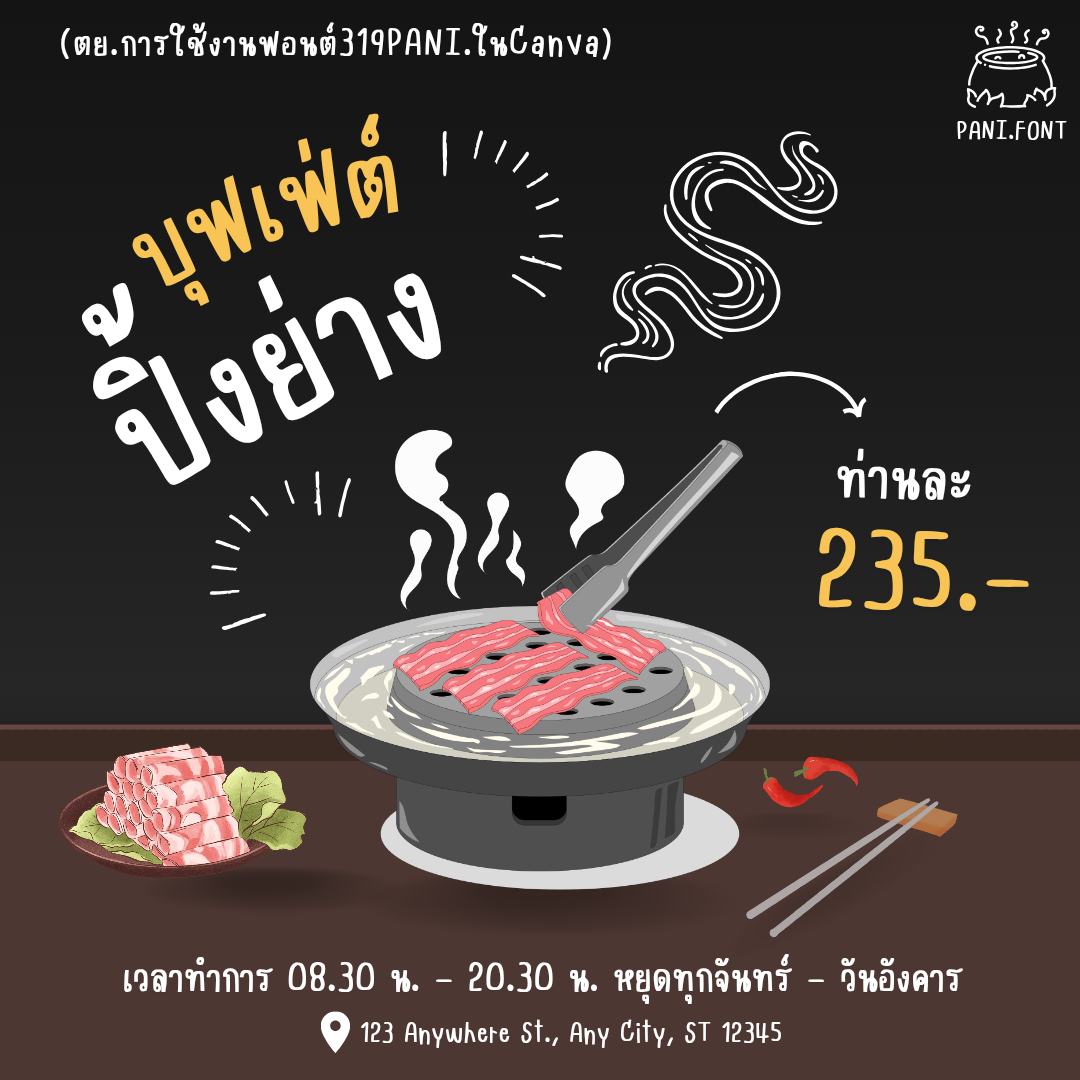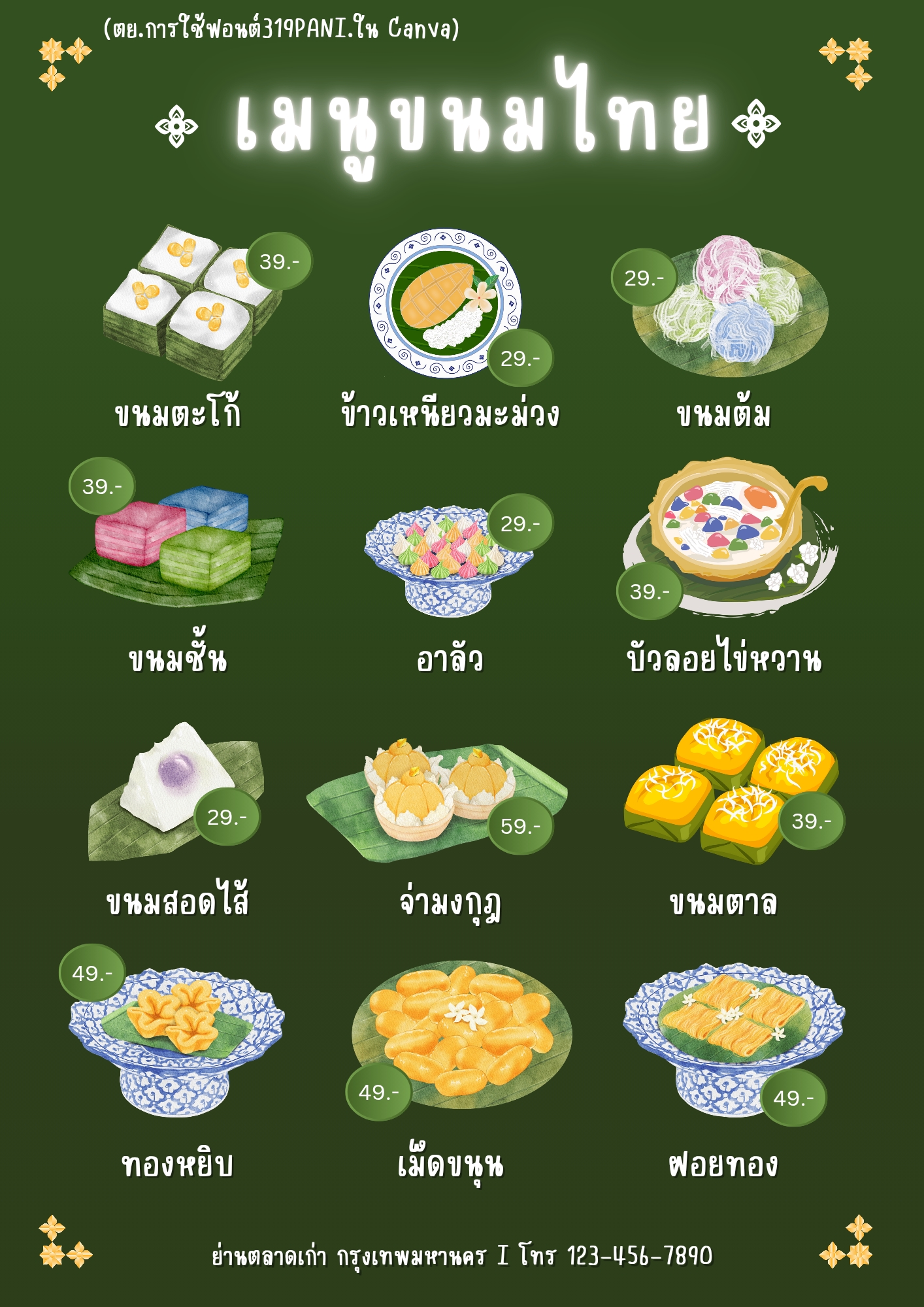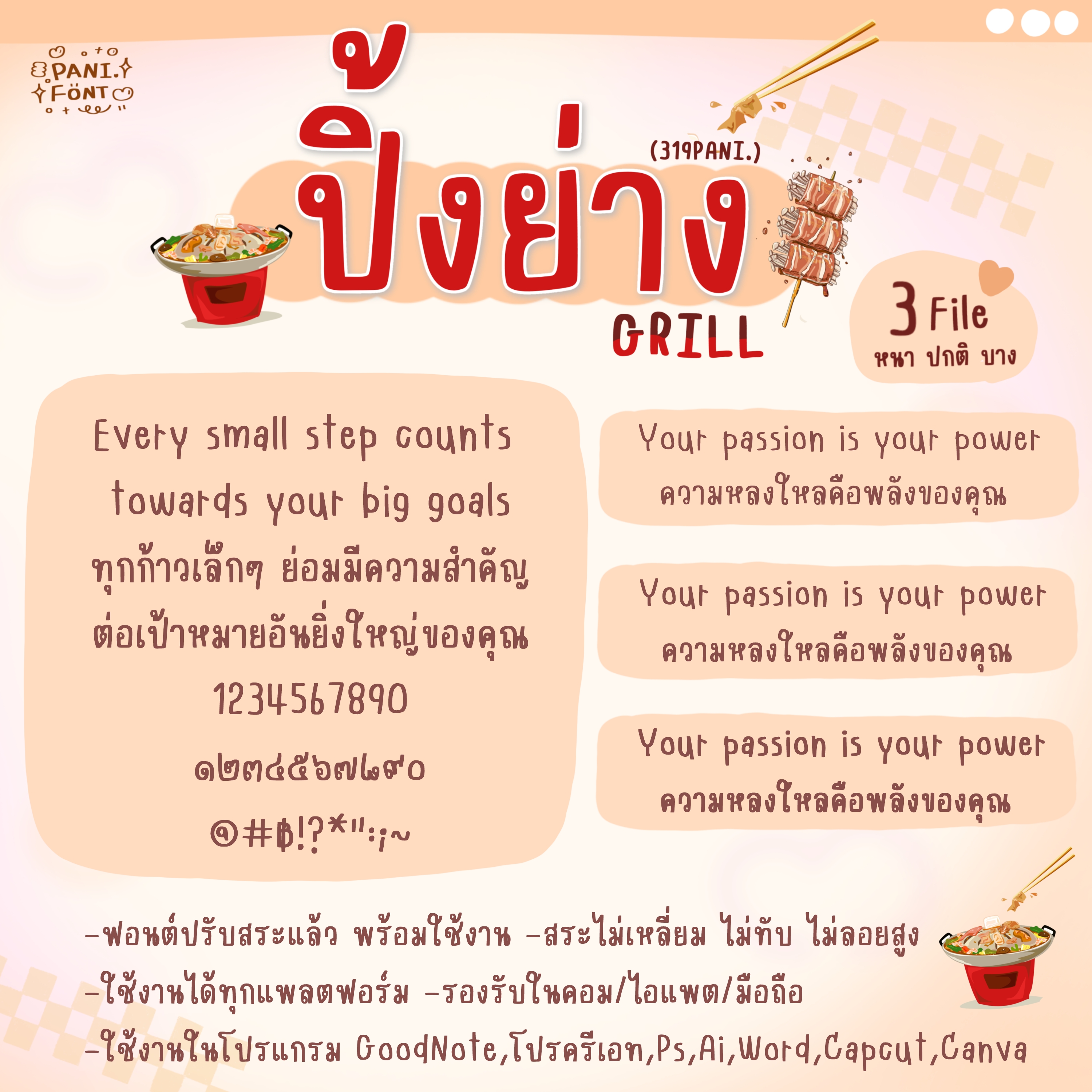
319PANI.ปิ้งย่าง
ฟอนต์ตัวธรรมดา ที่เรียบร้อย อ่านง่าย กำลังดี
ใช้งานได้หลายแนว สบายตา ดูพรีเมี่ยม!
จะใช้รายละเอียดเยอะๆ หรือเป็นหัวข้อก็สวยเด่น
สวยครบน้ำหนัก สายทำป้าย/ตั้งเครื่อง/จดโน๊ต
เป็นฟอนต์ที่ ควรมีลงคลังไว้เลือกใช้
ฟอนต์มี 3 ไฟล์ - น้ำหนัก บาง ปกติ หนา